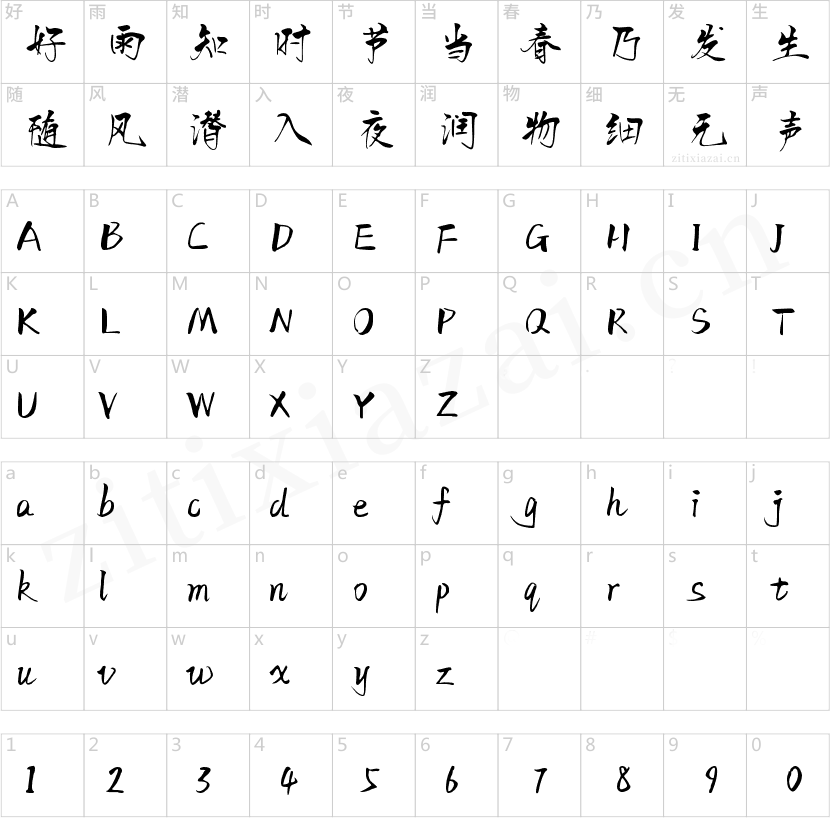
Aa秋螟体
Aa秋螟体字体
Aa秋螟体是一款非常具有艺术性的字体,它的设计灵感来源于对古典艺术的研究,同时又融入了现代字体设计的元素。字形优美,笔画粗细变化自然,给人以大气、典雅的感觉。Aa秋螟体是一款既传统又现代的字体,它的设计充满艺术感,美观大方,实用性也非常强。无论是对于设计师还是对于普通读者来说,都是一种非常不错的字体选择。Aa秋螟体适合用于具有艺术感的场合,比如海报、宣传单张、书籍封面等。由于其字形流畅且具有动态感,也适合用于大量的文本排版,如报纸、杂志等。